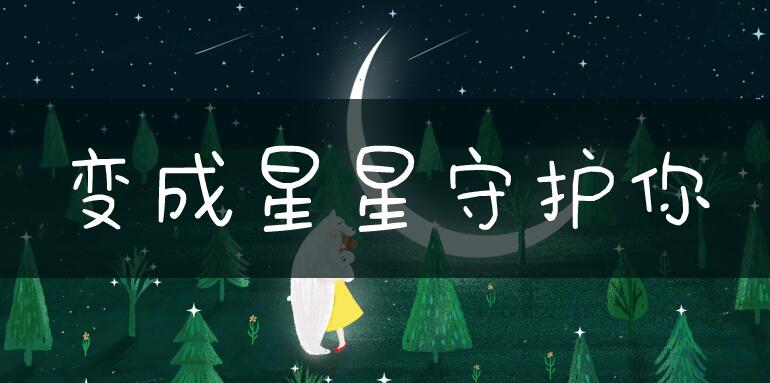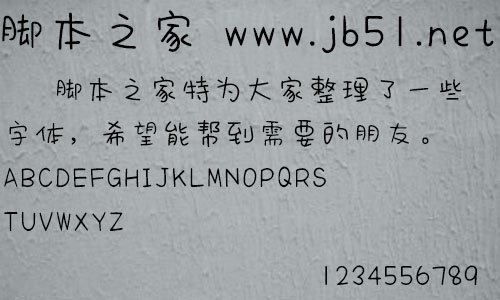
方正手跡-變成星星守護(hù)你由方正字庫(kù)俞亦婷設(shè)計(jì)師出品的一款藝術(shù)字體,字體多用圓角,字形大小錯(cuò)落自然,適合應(yīng)用于藝術(shù)設(shè)計(jì)、平面宣傳設(shè)計(jì)、網(wǎng)頁(yè)設(shè)計(jì),書法等領(lǐng)域。
方正手跡-變成星星守護(hù)你,這款字體多用圓角,字形大小錯(cuò)落自然,宛如夜空中的繁星可愛(ài)迷人。適用于少年兒童類書刊、品牌廣告包裝設(shè)計(jì),以及社交網(wǎng)絡(luò)的個(gè)性化用字。。。